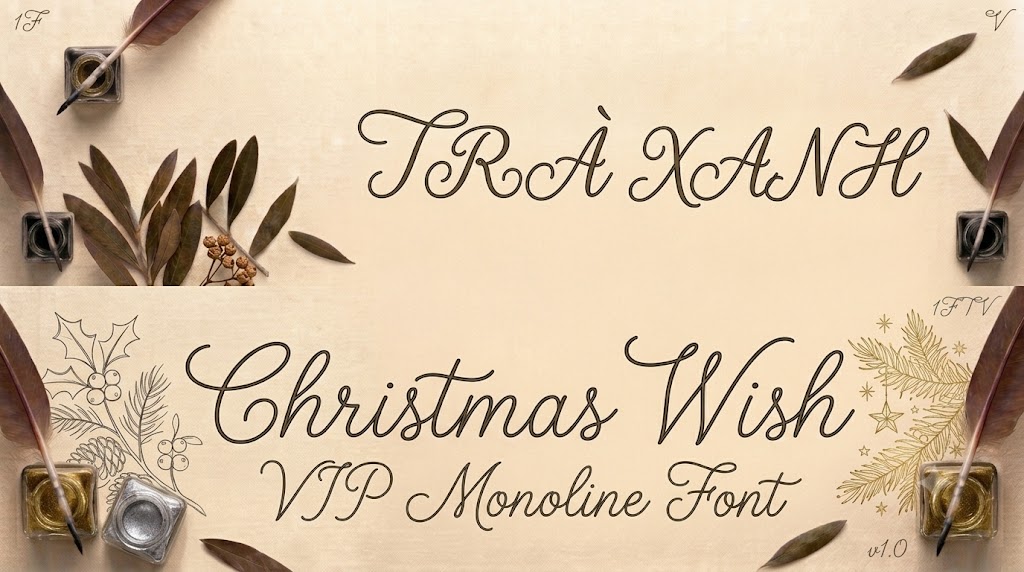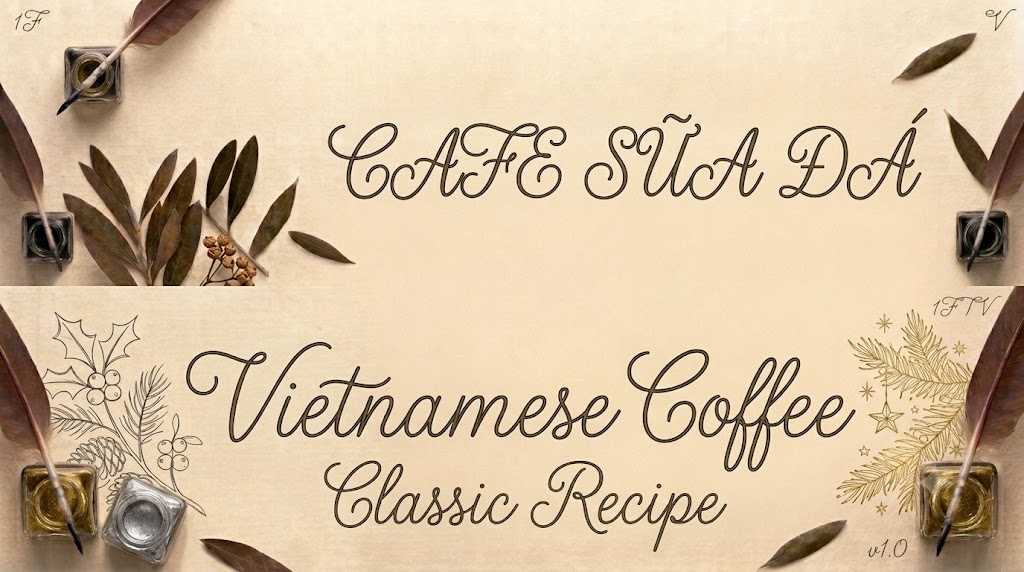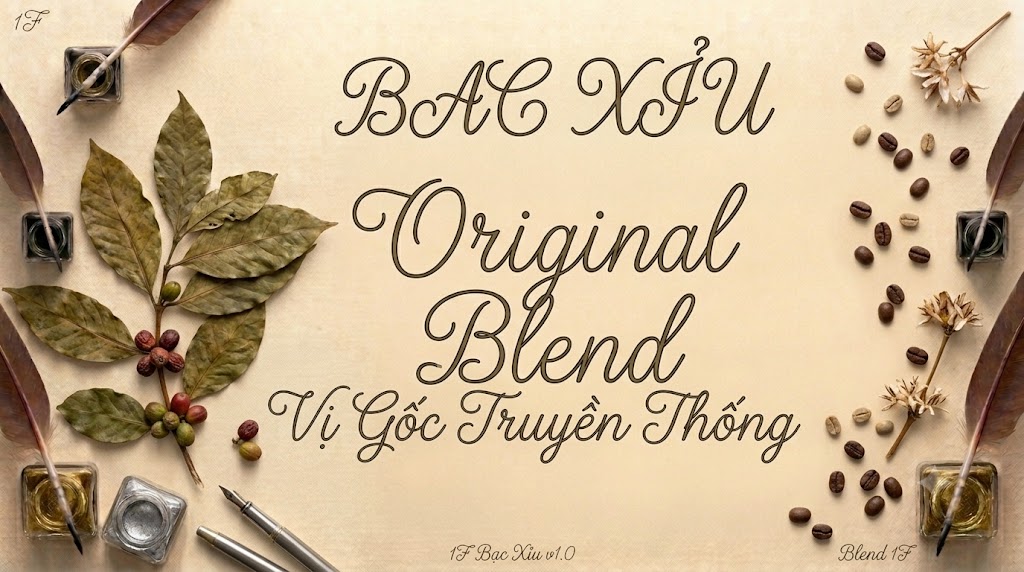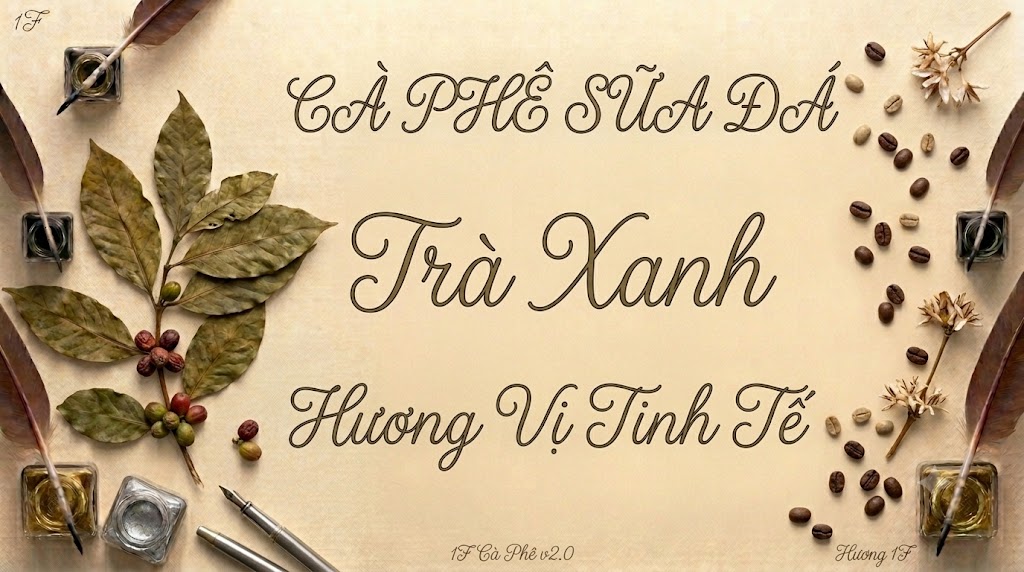
1FTV VIP Christmas Wish monoline
Bên cạnh những phông chữ hình khối dày dặn mang tính công nghiệp hiện đại, các thiết kế ngày nay vẫn luôn dành một vị trí trang trọng cho phong cách viết tay mềm mại, uyển chuyển.
Những nét chữ thanh mảnh, bay bổng giúp thổi hồn vào các tác phẩm nghệ thuật, mang lại cảm giác ấm áp, gần gũi và đong đầy cảm xúc.
Nếu bạn đang tìm kiếm một bộ font chữ nghệ thuật để chuẩn bị cho các dịp lễ hội, thiết kế thiệp mời hay làm tiêu đề video nhẹ nhàng, thì font 1FTV VIP Christmas Wish monoline chính là lựa chọn hoàn hảo.
Giới thiệu về font 1FTV VIP Christmas Wish monoline
Font 1FTV VIP Christmas Wish monoline là một phông chữ hiển thị dạng viết tay (script) mang đậm phong cách lãng mạn, thanh lịch và tinh tế.
Nhờ cấu trúc kỹ thuật đồng bộ này, phông chữ đảm bảo khả năng hiển thị vô cùng mượt mà, không bị vỡ nét hay răng cưa khi co giãn trên các phần mềm đồ họa.
Được thực hiện và chia sẻ rộng rãi bởi đội ngũ 1FTV, đây là giải pháp thiết kế tuyệt vời cho những ai đang tìm kiếm một nét chữ ký nghệ thuật độc đáo tại Việt Nam.
Đặc điểm nổi bật của phong cách thiết kế Christmas Wish monoline
Sức hút lớn nhất của font 1FTV VIP Christmas Wish monoline đến từ phong cách nét đều (monoline) kết hợp cùng những đường uốn lượn vô cùng điệu nghệ.
Độ dày của nét chữ được giữ đồng nhất từ đầu đến cuối, tạo nên một tổng thể vô cùng gọn gàng, mượt mà và mang tính tối giản hiện đại.
Các chữ cái viết hoa được tạo hình như những nét vẽ nghệ thuật bay bổng, trong khi bộ chữ cái thường sở hữu các đường nối mềm mại tạo cảm giác liền mạch như chữ ký tay.
Sự kết hợp hoa thường linh hoạt giúp dòng tiêu đề của bạn giữ được sự tự nhiên của ngôn ngữ, tạo cảm giác như một bức thư tay viết riêng đầy trân trọng.
Để phông chữ vận hành mượt mà trên hệ thống máy tính, phiên bản font 1FTV VIP Christmas Wish monoline đã trải qua quy trình xử lý thông số kỹ thuật kỹ lưỡng.
Hệ thống khoảng cách giữa các chữ và độ giãn dòng đã được căn chỉnh chuẩn xác, giúp các ký tự khi nối nét với nhau luôn giữ được sự liền mạch, hài hòa tuyệt đối.
Bên cạnh bộ chữ cái hoa và thường đồng bộ, phông chữ còn tích hợp đầy đủ dãy số từ 0-9 cùng hệ thống các ký tự đặc biệt, dấu câu thông dụng (.,;: ' " (!?) +-*/=).
Bản tối ưu này giúp các nhà sáng tạo nội dung hoàn toàn yên tâm thiết kế các văn bản tiếng Việt mà không lo gặp phải tình trạng lỗi hiển thị hay lệch dấu.
Hình ảnh demo thực tế của font 1FTV VIP Christmas Wish monoline
Để giúp bạn dễ dàng hình dung khả năng co giãn và hiển thị linh hoạt của phông chữ này trên các kích thước khác nhau, hãy cùng xem qua bảng mô phỏng thực tế:
Kích thước nhỏ (12pt – 24pt): Các nét chữ thanh mảnh và bộ chữ viết tay vẫn hiển thị rất rõ ràng, ngay ngắn, tinh tế trên màn hình điện thoại di động.
Kích thước lớn (36pt – 72pt): Đây là không gian lý tưởng để font chữ phô diễn toàn bộ sự bay bổng nghệ thuật, tạo hiệu ứng thị giác lãng mạn cho các tiêu đề chính.
Ứng dụng của font Christmas Wish monoline trong thiết kế đồ họa và làm video
Sở hữu nét cá tính lãng mạn và cấu trúc viết tay mềm mại, font 1FTV VIP Christmas Wish monoline mở ra không gian ứng dụng rộng lớn cho các dự án truyền thông:
Thiết kế thiệp mời và thiệp chúc mừng lễ hội: Hoàn hảo để làm thiệp mời đám cưới, thiệp chúc mừng Giáng sinh, năm mới hoặc các sự kiện mang tính chất ấm áp, sang trọng.
Làm tiêu đề video ngắn (Tiktok, Shorts, Reels): Rất thích hợp cho các video thuộc chủ đề vlog đời sống, kể chuyện tâm sự, làm thơ hoặc chia sẻ các thông điệp nhẹ nhàng, sâu lắng.
Thiết kế ảnh thu nhỏ mạng xã hội phong cách nghệ thuật: Thích hợp cho các thumbnail Youtube về chủ đề âm nhạc acoustic, review sách, phim ảnh hoặc phong cách sống tối giản.
Nhận diện thương hiệu và bao bì sản phẩm nghệ thuật: Phù hợp làm logo dạng chữ ký, thiết kế nhãn mác cho các tiệm hoa, thương hiệu mỹ phẩm hữu cơ, tiệm bánh ngọt hay các quán cà phê lãng mạn.